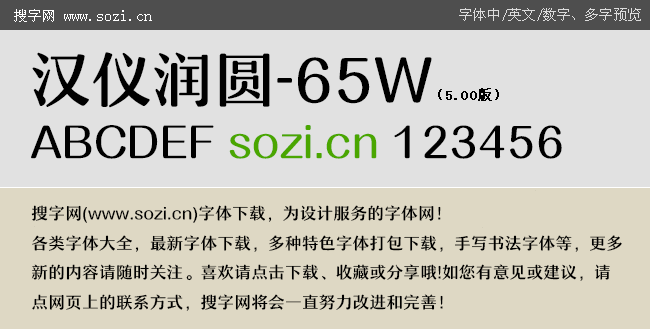
漢儀潤(rùn)圓-65W
搜字網(wǎng)提供一漢儀潤(rùn)圓-65W中文字體下載,漢儀潤(rùn)圓字體是源于在圓體的基礎(chǔ)上,加入黑體,宋體的元素特征創(chuàng)新而成,力求打造一款穩(wěn)重大氣輕松優(yōu)雅的家族字體。適合應(yīng)用于廣告設(shè)計(jì)、名片設(shè)計(jì)、包裝印刷、產(chǎn)品設(shè)計(jì)等應(yīng)用。